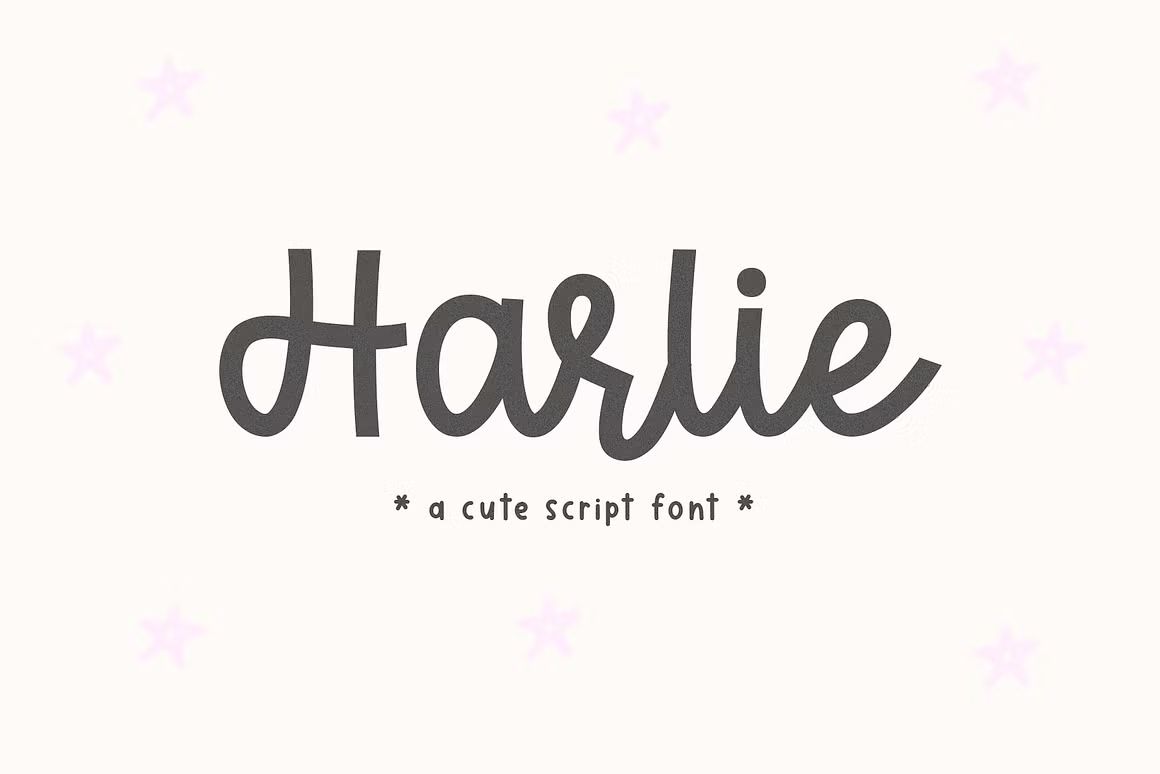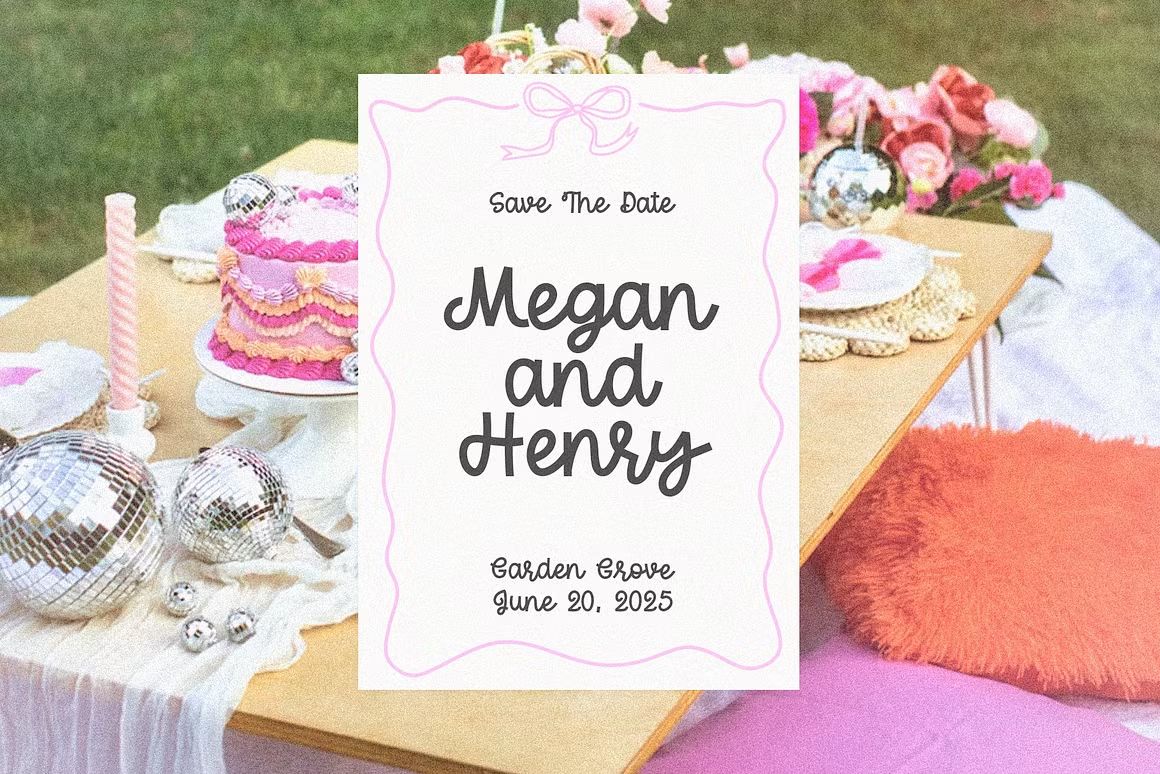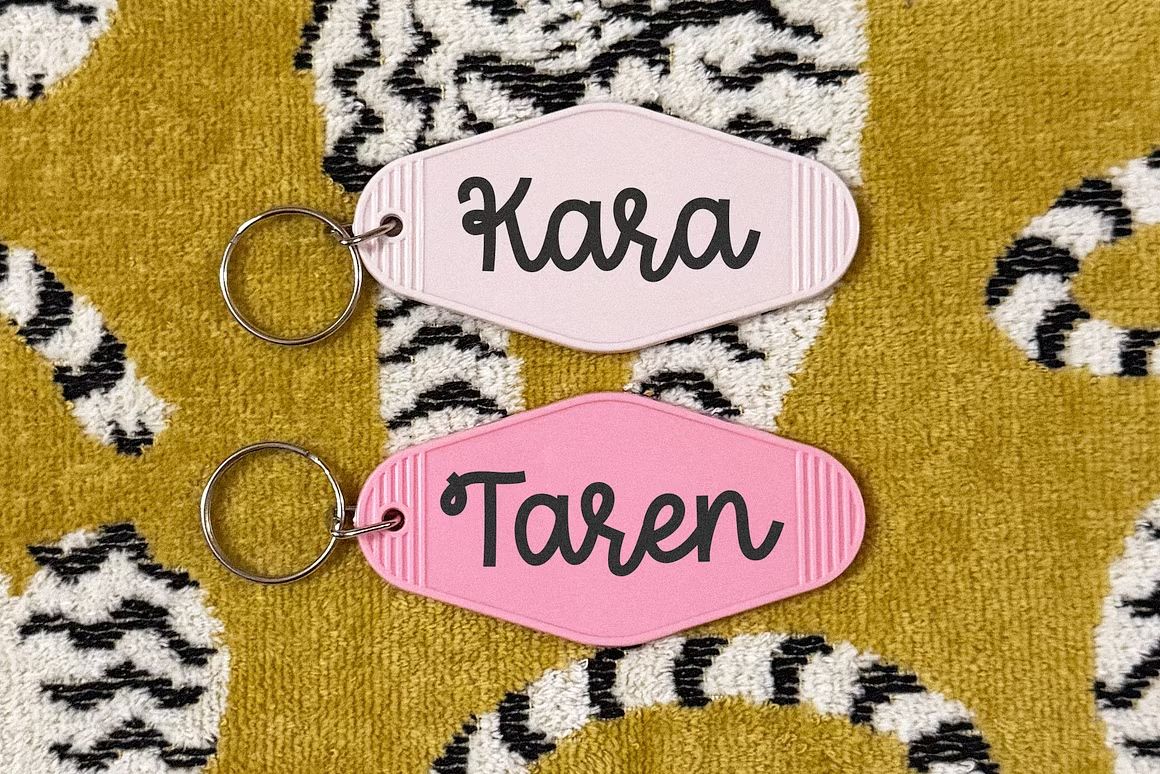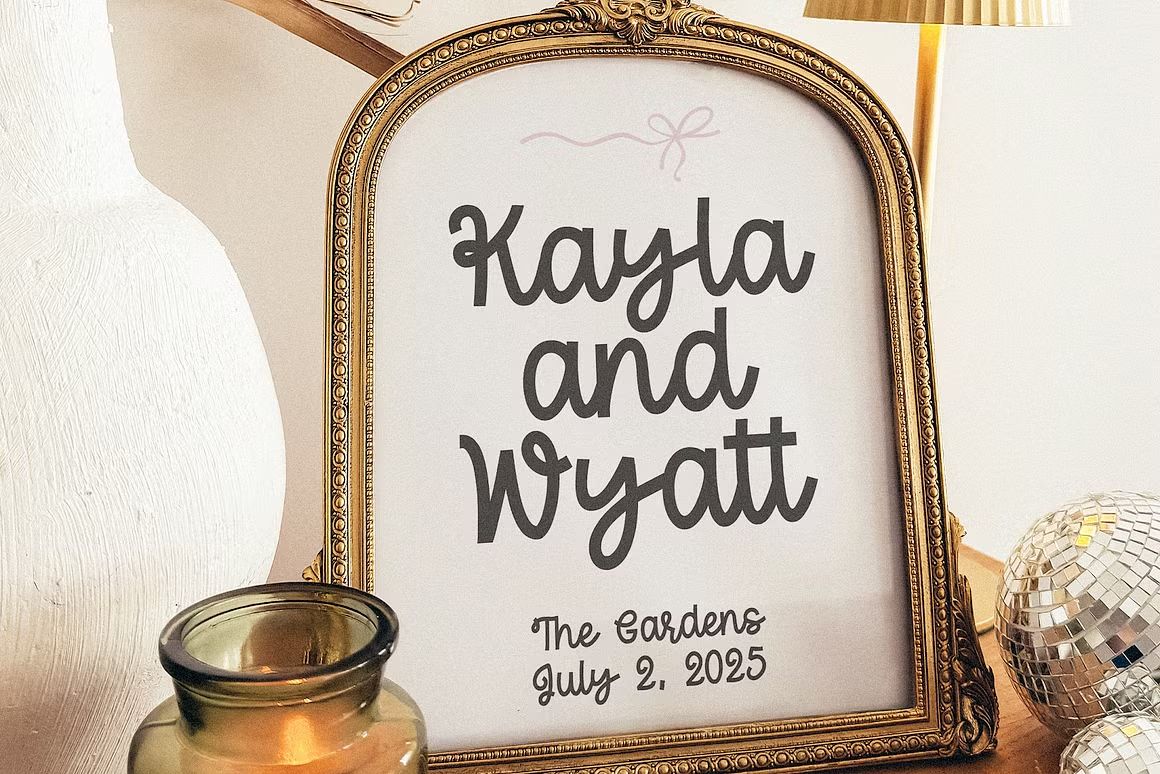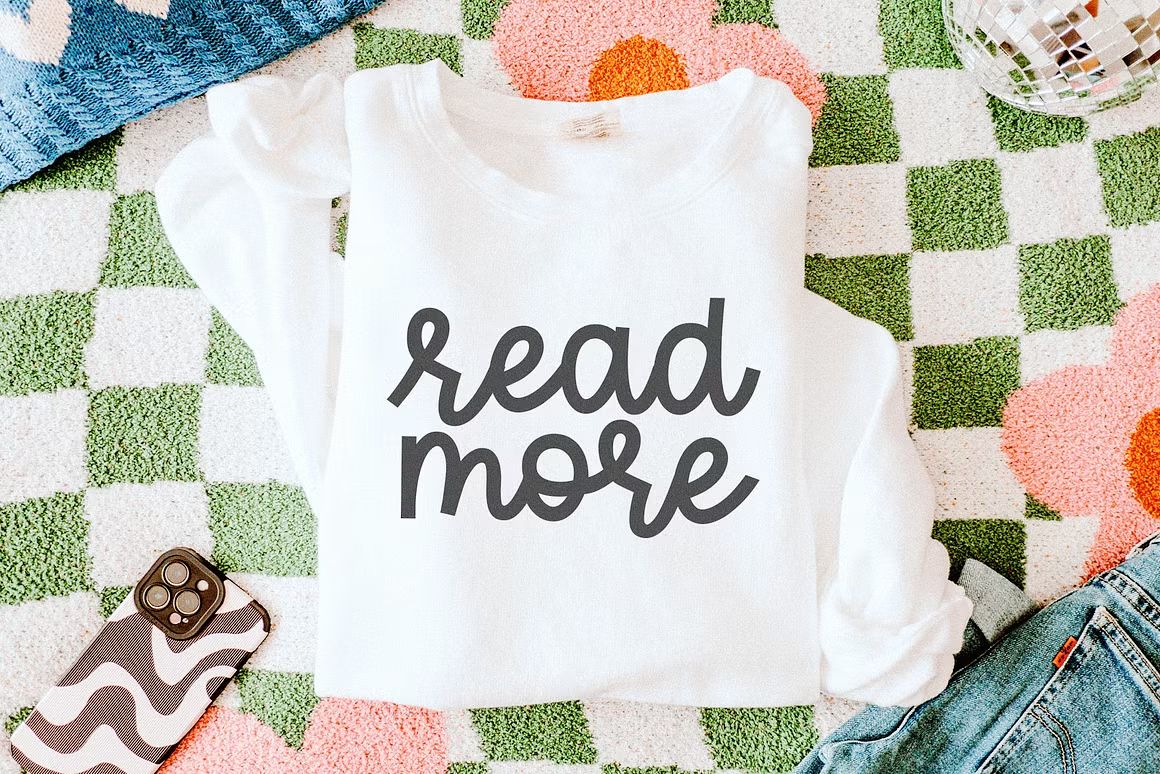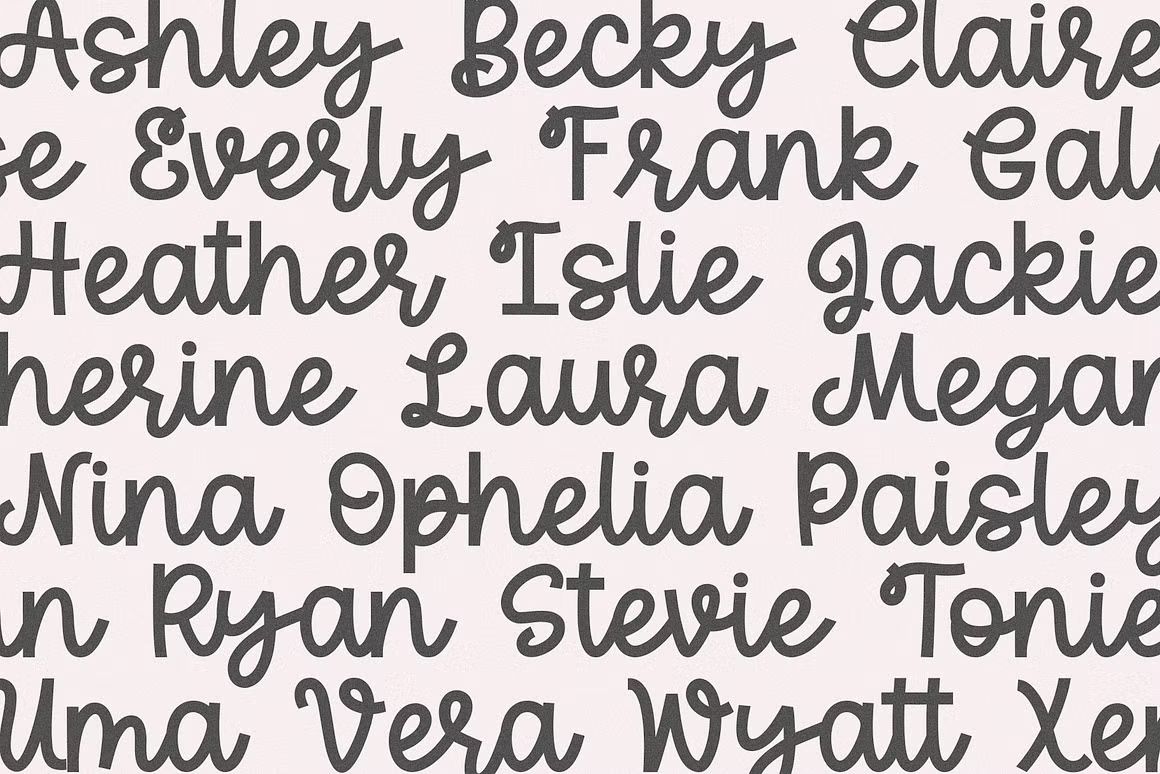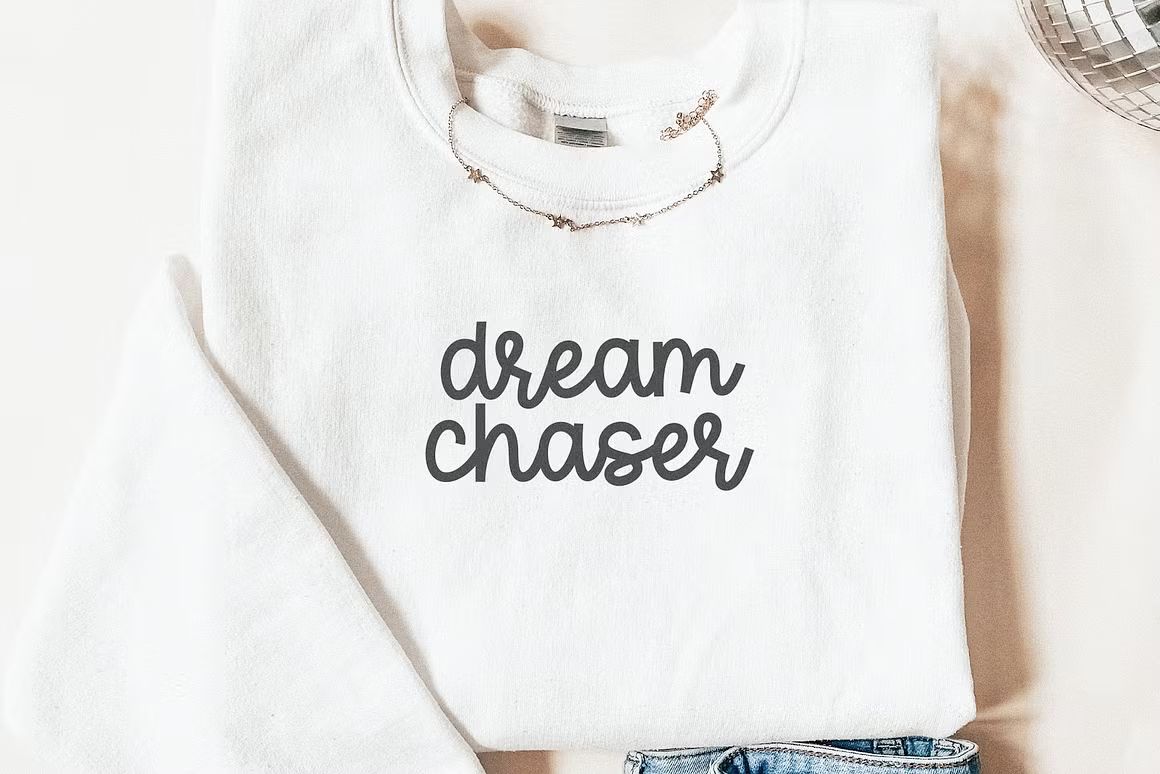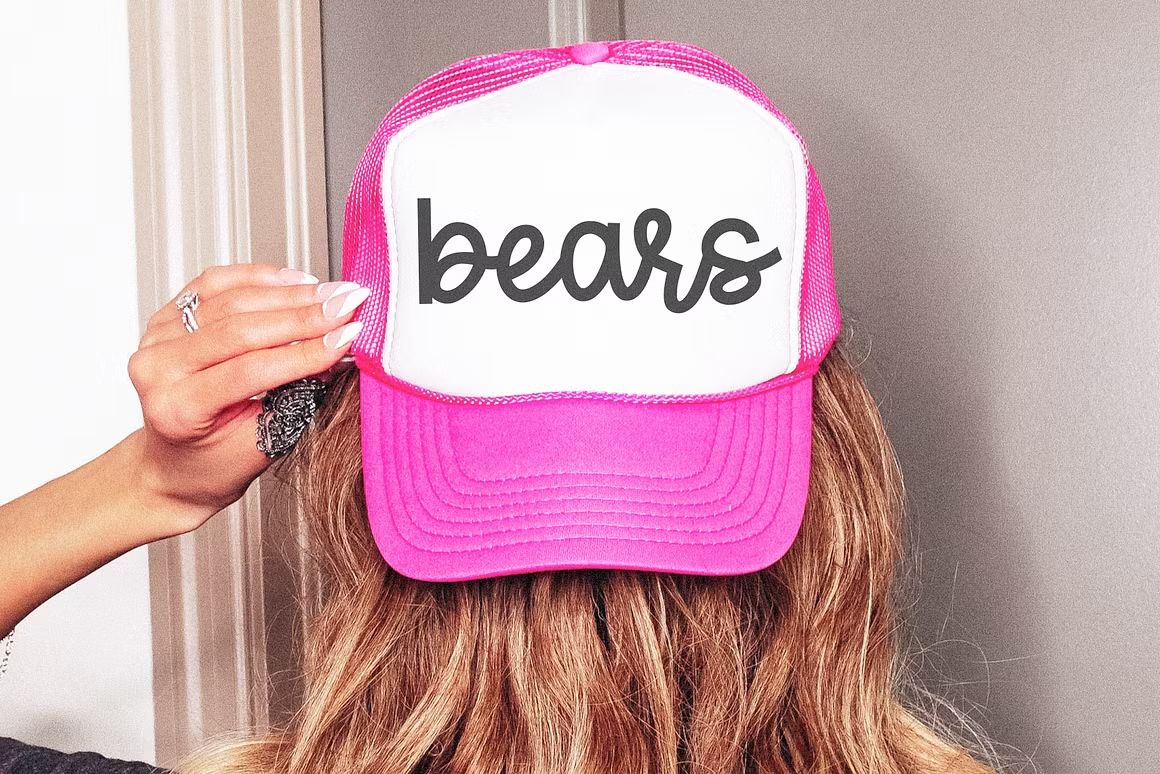
Harlie – Cute Script Font
Harlie adalah font cute script dengan gaya tulisan tangan yang playful dan imut, sempurna untuk desain kartu ucapan, logo, branding, dan proyek kreatif yang menginginkan tampilan ceria dan menggemaskan.
Harlie adalah font cute script dengan desain tulisan tangan yang ceria dan penuh karakter. Dengan lekukan halus dan sentuhan playful, font ini cocok untuk berbagai proyek kreatif seperti kartu ucapan, logo, branding, dan desain yang menginginkan nuansa imut dan menggemaskan. Harlie memberikan kesan yang menyenangkan dan personal pada setiap karya desain Anda.
Fitur unggulan:
• Gaya script tulisan tangan yang imut dan playful
• Cocok untuk kartu ucapan, branding, logo, dan desain ceria
• Termasuk huruf besar, huruf kecil, angka, dan simbol lengkap
• Ideal untuk proyek cetak dan digital yang membutuhkan nuansa menyenangkan dan imut